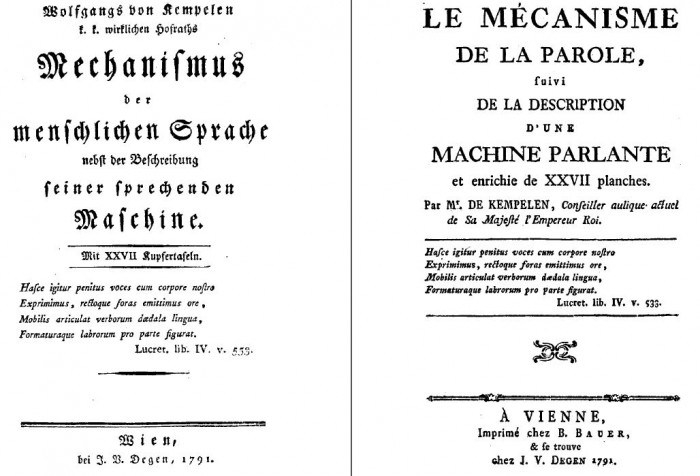
Parallelausgabe mit versch. Linien
folgende Frage: Der "Mechanismus der menschlichen Sprache" des Wolfgang von Kempelen erschien 1791 sowohl in einer deutschen wie einer französioschen Ausgabe. Beide erschienen im selben Verlag und wurden vom selben Drucker hergestellt.
Trotzdem unterscheiden sich die Titelblätter in ihrer Gestaltung ganz erheblich. Insbesondere die Ausschmückung mit Linien und Ornamenten ist bei der französischen Fassung erheblich opulenter (siehe Bild).
Was kann das für Gründe haben? Lag die Ausschmückung im Ermessen des jeweiligen Setzers? Oder gibt es einen Zusammenhang zwischen der Schmuckgestaltung und der Schrifttype (Fraktur vs. Antiqua)? Oder trug man unterschiedlichen Verzierungstraditionen in Frankreich udn Deutschland Rechnung? Oder...
Ich besitze zu wenige Bücher aus dem 18. Jahrhundert, doch für das 19. spiegeln beide meiner Meinung nach die Mode der beiden Länder wider.
Interessant finde ich die optische Nutzung der ch-Ligatur.
Oder gibt es einen Zusammenhang zwischen der Schmuckgestaltung und der Schrifttype (Fraktur vs. Antiqua)? Oder trug man unterschiedlichen Verzierungstraditionen in Frankreich udn Deutschland Rechnung? Oder...
Sicherlich eine Kombination aus all dem. So würden wir Gestalter es heute auch noch machen. Es gab und gibt gewisse regionale und stilbedingte Konventionen und denen versucht man in der Gestaltung zu entsprechen, so dass der Gesamteindruck für den Leser vertraut und somit »stimmig« ist.
Solche Details, warum einmal eine durchgezogene, und einmal eine etwas verzierte Linie gewählt wurde, wird man sicherlich heute kaum noch klären können.
Ich besitze zu wenige Bücher aus dem 18. Jahrhundert, doch für das 19. spiegeln beide meiner Meinung nach die Mode der beiden Länder wider.
Interessant finde ich die optische Nutzung der ch-Ligatur.
Könnte es damit zusammenhängen, dass manche Wörter gesperrt gesetzt sind und bei diesen dann auch die Ligatur aufgelöst wurde?